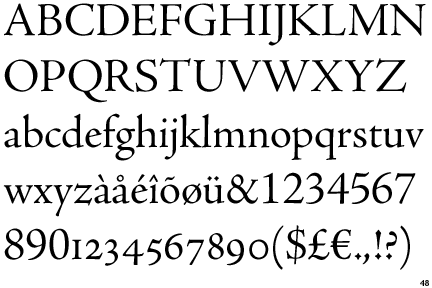
ich kann mich auch irren, aber die super-schrägen ohrwascheln des »T« riechen förmlich nach renaissance-antiqua.
Guck mal beim Eichhörnchen (oder Google) nach Calluna, Crimson oder Ghandi.
Es ist keine Garamond und keine Centaur, aber nahe drann. Wie wäre es damit als weiteren Vorschlag?
Adobe Jenson Pro Subhead
Designed for use at sizes from 13 to 22 points.
One of a set of Optical Sizes with the fonts Adobe Jenson Pro Display, Adobe Jenson Pro and Adobe Jenson Pro Caption.
Möglicherweise gibt es ähnlichere Versionen?